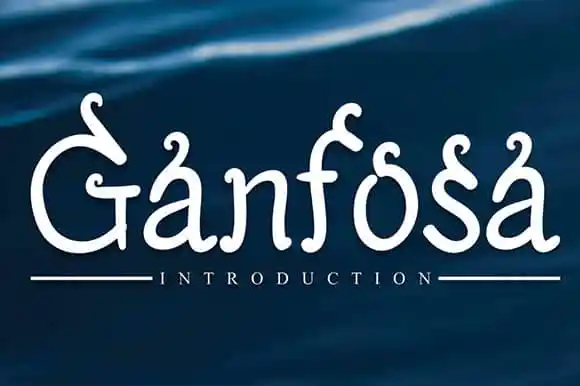
Ganfosa Display Font – Download Grátis
A fonte Ganfosa Display é uma escolha ideal para os designers que procuram se destacar em projetos decorativos. Com seu estilo elegante e moderno, ela oferece a oportunidade de personalizar qualquer projeto com um toque sofisticado. Perfeita tanto para aplicações outdoor como para itens pessoais, esta fonte é perfeitamente adaptada a uma variedade de aplicativos, desde postes publicitários até embalagens de produtos ou mesmo cartões de visita e materiais de escritório. Suas linhas retas e detalhes elaborados tornam-na um recurso indispensável para quem busca expressar elegância em seu trabalho. Com Ganfosa Display Font, você consegue criar uma identidade visual única em qualquer projeto que exige um toque delicado de graça. Engana-se quem pensa que a Ganfosa Display é apenas um design formal; ela também tem capacidades versáteis para adaptar seus traços aos estilos mais criativos e contemporâneos, tornando-a uma fonte indispensável na sua coleção.